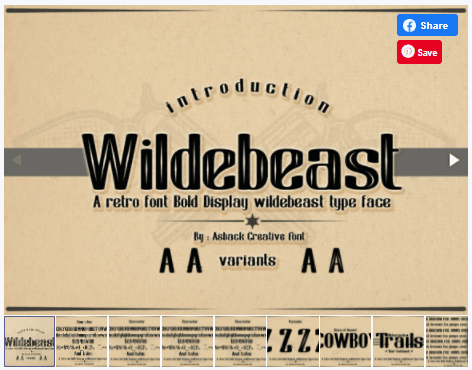
Wildebeast Font
Wildebeast - это крутой дисплейный шрифт в винтажном стиле. Независимо от того, используете ли вы его для поделок, цифрового дизайна, презентаций или создания поздравительных открыток, этот шрифт может стать вашим любимым шрифтом в любом случае!